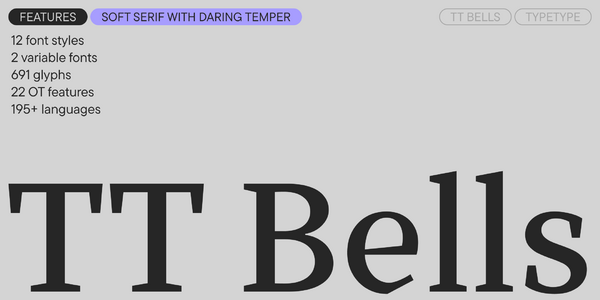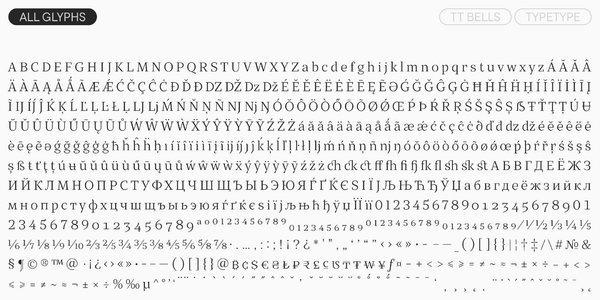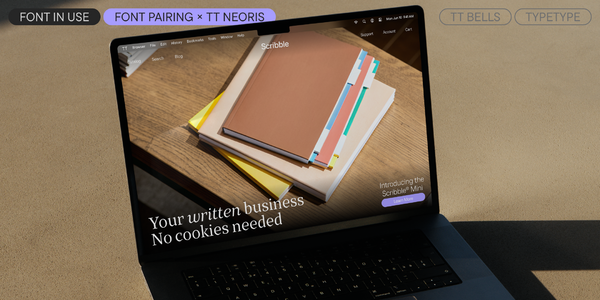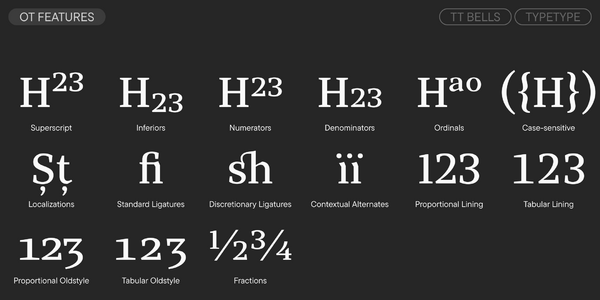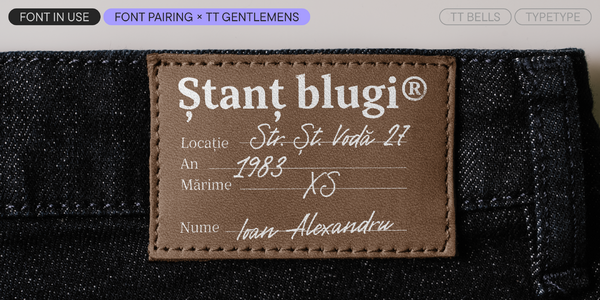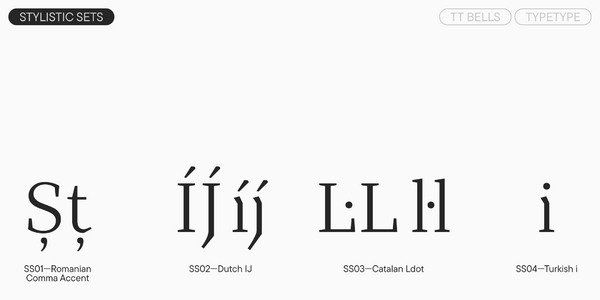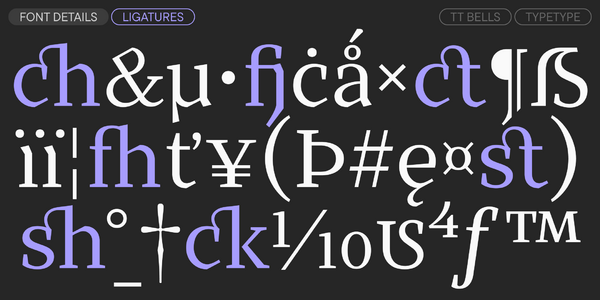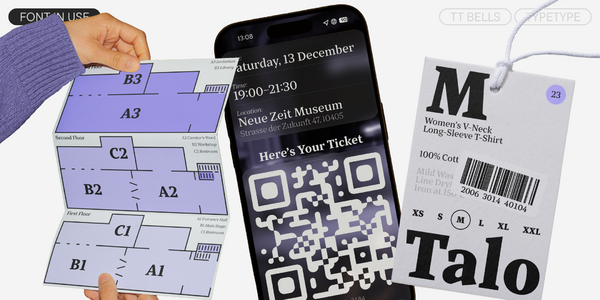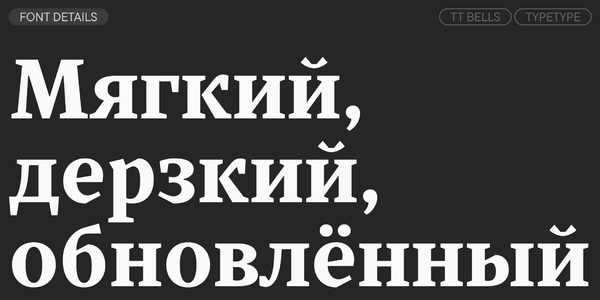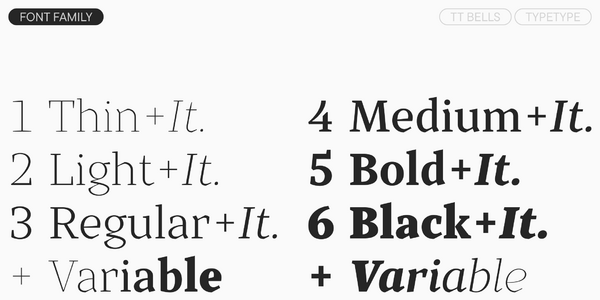
TT Bells
TT Bells — ТТ Белс
Произносится «ТТ Белс». «Bells» — производное слово от bell, в переводе с английского «колокол». Буквы «TT» являются аббревиатурой названия компании.
TT Bells — антиква, в которой элегантная мягкость сочетается с непростым и дерзким характером. Подходит для заголовков и текстового набора.
TT Bells
Элегантная мягкость антиквы с дерзким характером
TT Bells
Мы взяли самое лучшее из старостильных шрифтов, созданных в доцифровую эпоху, и добавили в этот традиционный стиль острые и современные геометрические приемы. Таким образом TT Bells отсылает зрителя и любителей шрифтов к истокам, но при всем при этом напоминает, что мы живем в цифровую эру, где миром правит геометрия и экраны.
При уменьшении кегля его резкость и дерзость смягчается, шрифт становится более классическим
TT Bells подходит для разных flask видов текста
О гарнитуре TT Bells
Встречайте TT Bells версии 3.000!
Обновили шрифт, добавив новые начертания, знаки, фичи и языки, а также усовершенствовали техническую составляющую.
TT Bells — антиква, в которой элегантная мягкость сочетается с непростым дерзким характером. Он выражается в прямых срезах и клинообразных засечках, характерных для старостильных шрифтов.
В TT Bells мы сохранили все лучшие черты традиционного стиля, но добавили острые элементы и современные геометрические приёмы. Поэтому рисунок шрифта одновременно отсылает к истокам и выглядит современно, напоминая о том, что мы живём в цифровую эпоху.
В обновлённую версию мы добавили четыре новых начертания: Medium, Medium Italic и два вариативных (прямое и наклонное), меняющихся по оси жирности. Расширили кассовый состав — дорисовали знаки для расширенной латиницы, знаки валют и дроби. Также добавили новые языки и OpenType фичи, заново сделали хинтинг и кернинг.
TT Bells подходит для разных задач: его можно использовать как в акцентных надписях, так и в массивах текста. При уменьшении кегля резкость и дерзость шрифта смягчается, он приобретает более классический вид и сохраняет читабельность.
TT Bells 3.000 — это:
• 14 начертаний: 6 прямых, 6 наклонных и 2 вариативных шрифта;
• 691 знак в каждом начертании;
• 22 OpenType фичи;
• Поддержка 195 языков.
Что изменилось в шрифте:
• Количество начертаний увеличилось с 10 до 14: появились четыре новых начертания — Medium, Medium Italic и два вариативных (прямое и наклонное), меняющихся по оси жирности;
• Количество знаков в каждом начертании увеличилось с 540 до 691, в том числе появились знаки для расширенной латиницы, знаки валют и дроби;
• Количество OpenType фич увеличилось с 15 до 22;
• Количество языков увеличилось со 160+ до 195;
• Полностью обновились хинтинг и кернинг.
liga | Standard Ligatures
dlig | Discretionary Ligatures
onum | Oldstyle Figures
case | Case Sensitive Forms
ss02 | Dutch IJ
ss03 | Catalan Ldot